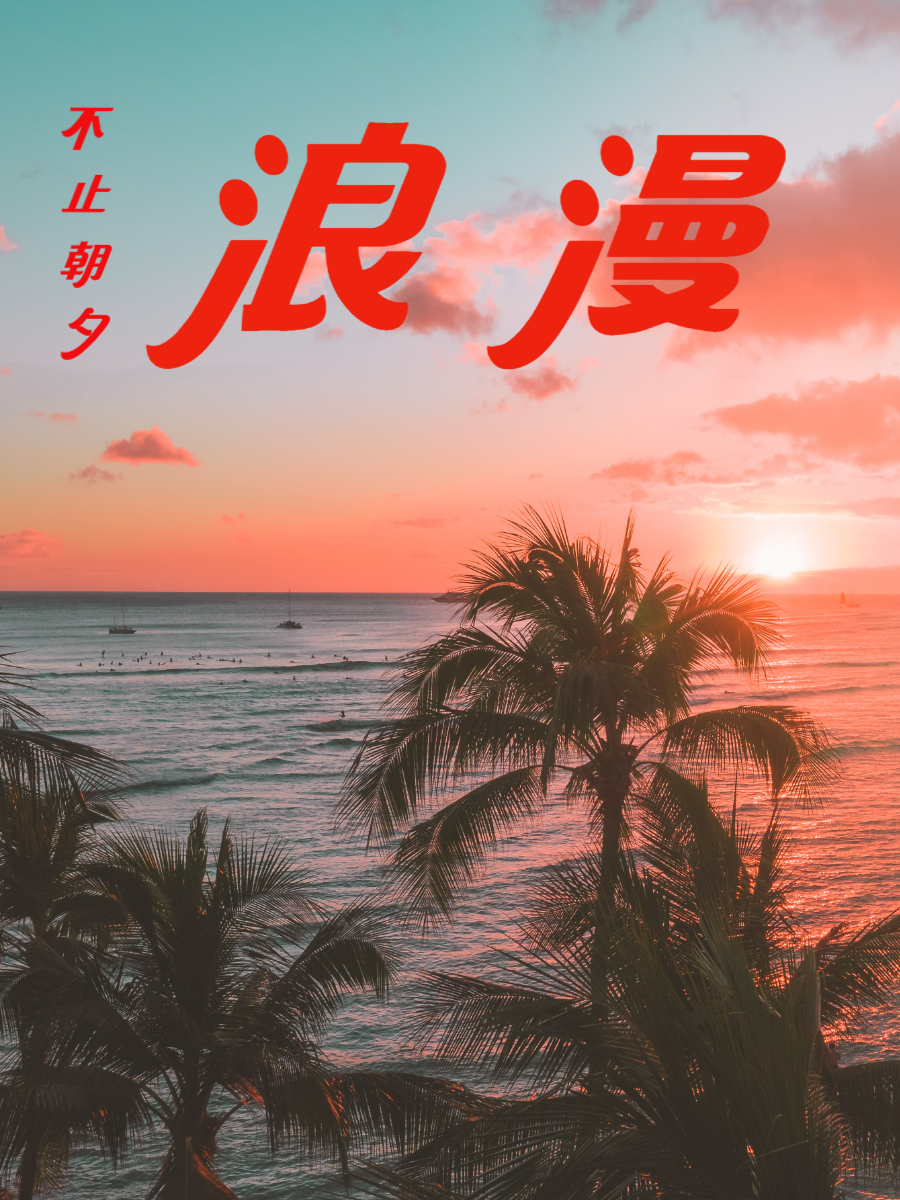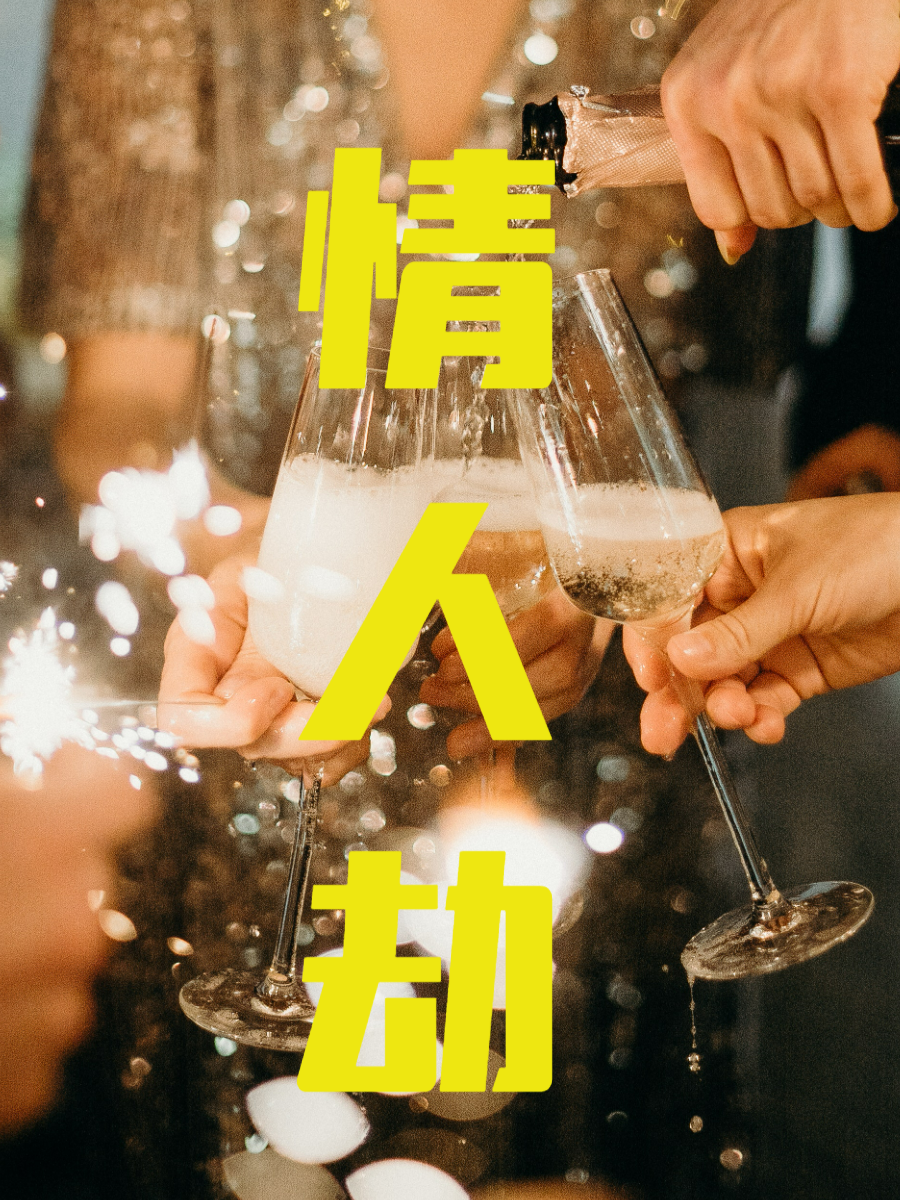
中国式浪漫!一键获取属于我们中国人自己的七夕情人节字体吧!
又是一年七夕到,在这个被爱意围绕的浪漫节日,你有怎样的计划?七月初七,“牛郎织女”通过鹊桥相会的美丽爱情传说,因此有了“七夕”这个最具浪漫色彩的传统节日。在这个美好的日子,甜蜜氛围感都拉满了!
励字造梦共创字库助你爱的力量,精选2款七夕情人节字体,跨越山海时空,依然相信爱情!
采用中西结合的设计手法,一方面糅合西文斜体装饰风格的浪漫优雅,字体倾斜112度;一方面运用汉字隶书笔画的撇、捺错落变化,在蚕头燕尾的韵味中,构建斜体字的韵律感、节奏感;在微妙的平衡感中,创造轻松明快的自洽节奏,也是对字体美感的均衡把控。
横看成岭侧成峰,“磅礴黑”实验性地采用斜体与正体的融合,左侧倾斜的手法在整体稳重大气的字形中增添少许灵动,右侧的垂直设计支撑起整个架构,形成“气势磅礴,万壑争流”之势,不禁感叹“不识庐山真面目,只缘身在此山中”。